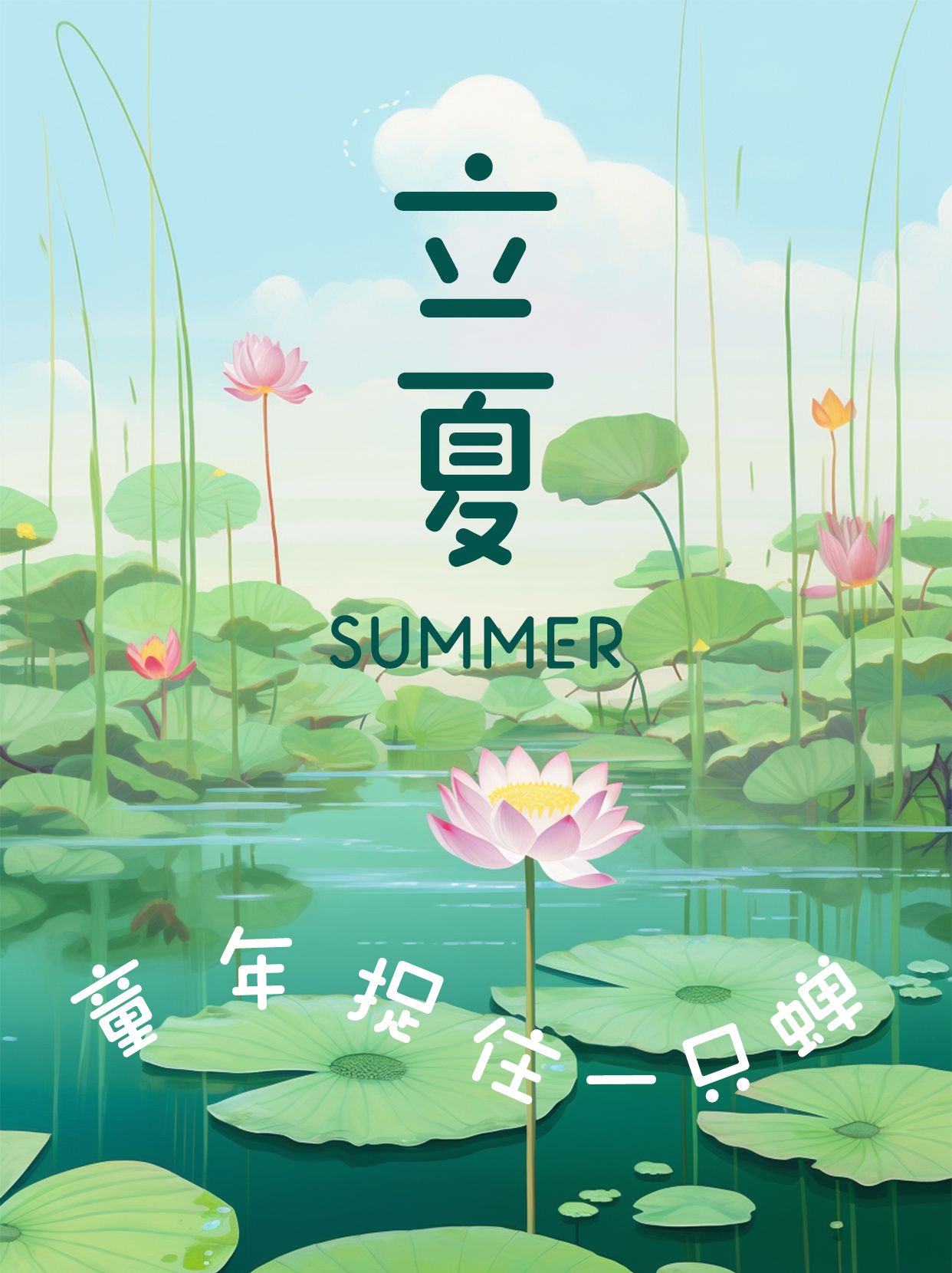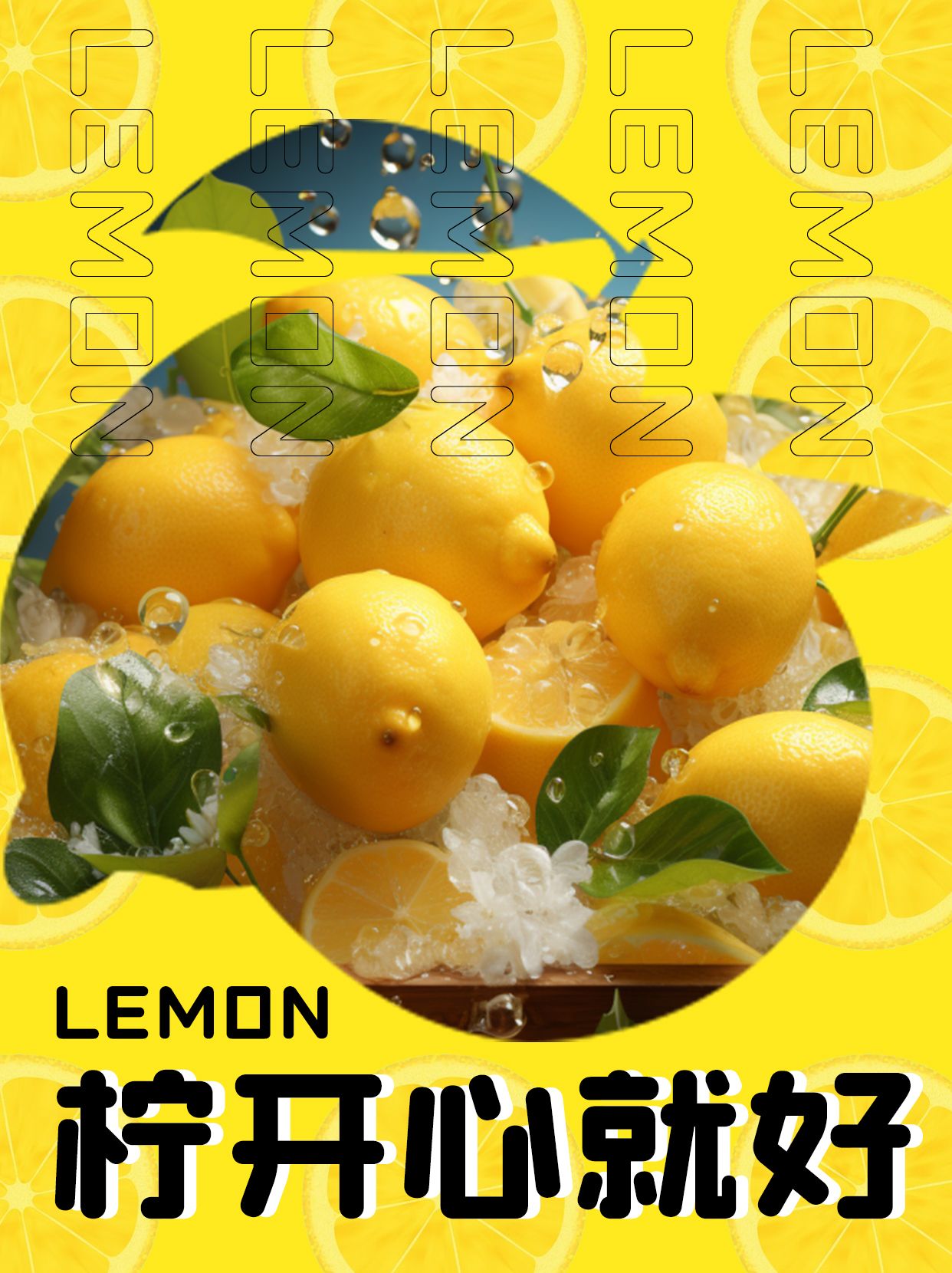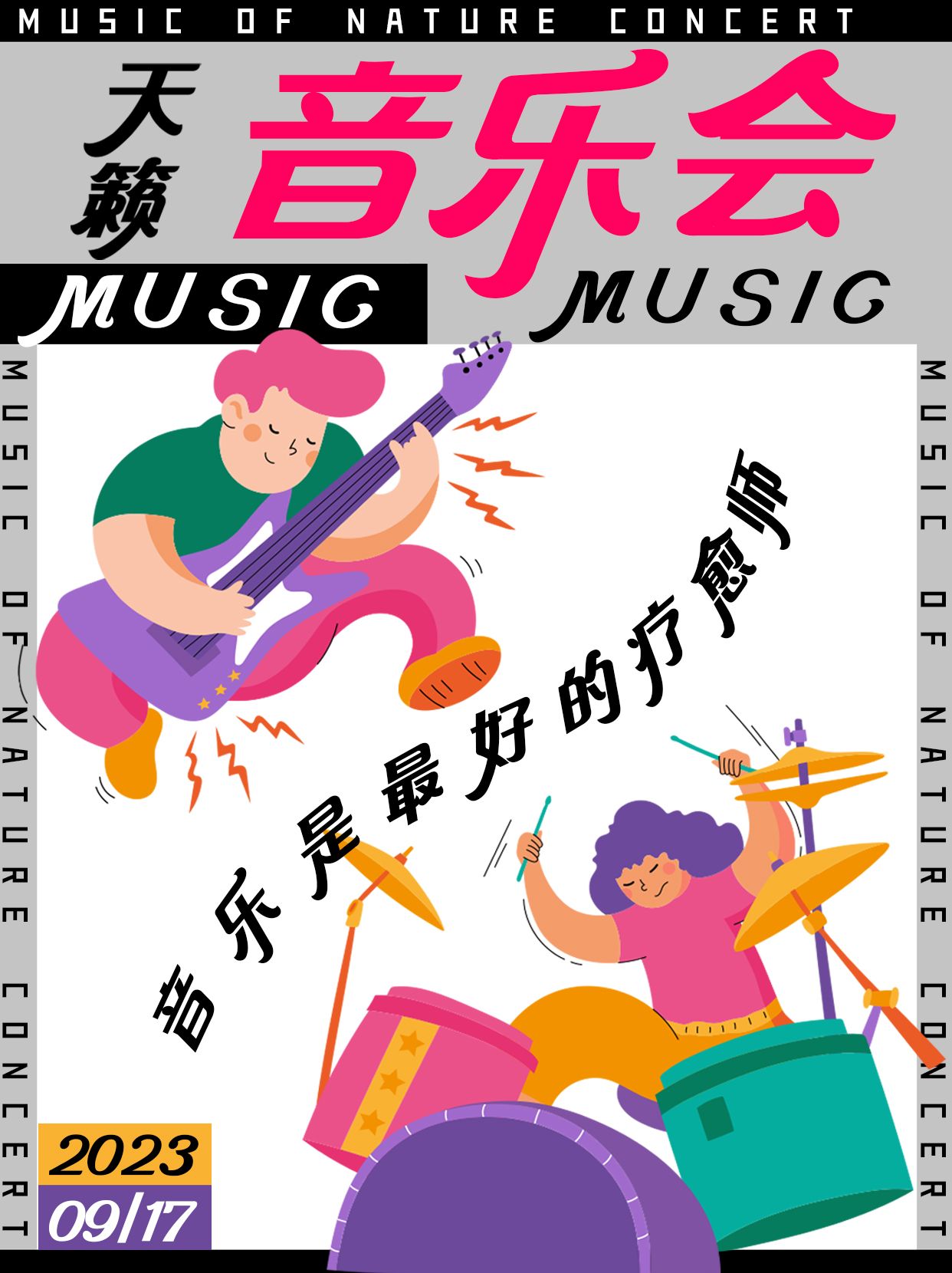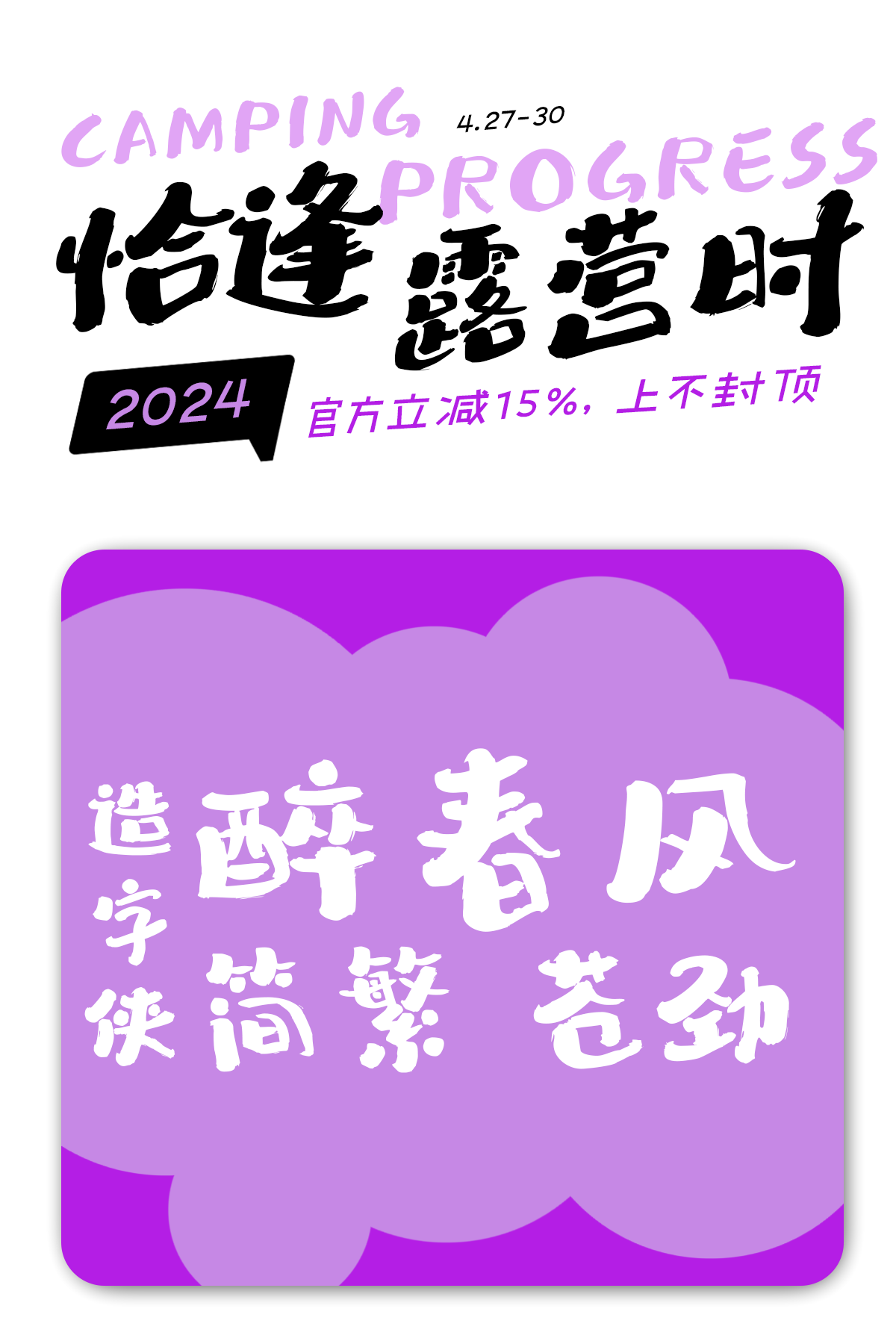
让你的文字瞬间萌化人心:可爱字体推荐
在数字化时代,字体不仅是文字的载体,更是情感的传递者。外形可爱的字体以其独特的魅力,为文字增添了一份童真与趣味,让人们在阅读、观赏时感受到温暖与愉悦。今天,就让我们一起走进可爱字体的世界,探索那些能让文字瞬间萌化人心的神奇字体吧!
励字小桃气简繁 常规圆,是一款独特而富有创意的圆体。它字型上松下紧,重心略低,结构松弛灵活,笔形圆润饱满且舒展流畅。该字体将现代审美与传统字型相融合,适用于各类创意设计。
造字侠郝刚快乐简 微黑,外形简洁明快,充满活力。独特的笔触设计,使得每个字都充满动感和生命力。适用于多种场合,无论是海报设计还是品牌标识,都能传递出积极向上的快乐氛围。
励字圆梦简 常规,字形简洁而不失力量,凝聚着梦想与激励。励字圆梦简 常规设计独特,线条流畅且富有张力,能够充分表达积极向上的情感。无论是用海报设计还是品牌标识,励字圆梦简 常规都能完美展现积极向上的精神风貌。
造字侠醉春风简繁 苍劲,手写字体独具韵味,融合了古典与现代之美。其笔画苍劲有力,给人以霸气的印象也不失活泼可爱的感觉。造字侠醉春风简繁 苍劲不仅展现了汉字的深厚底蕴,也彰显了独特的个性化设计。无论应用于广告、书籍还是品牌标识,都能给人留下深刻印象。
以上四款可爱字体各具特色,各有千秋。无论你是需要为作品增添一抹童趣,还是想让文字更具亲和力与感染力,这些可爱字体都能为你带来意想不到的效果。快来试试吧!